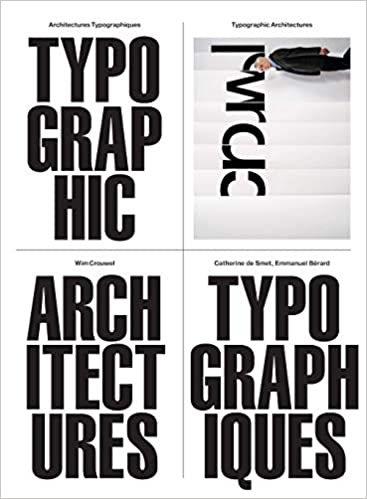
Architectures typographiques. Cet ouvrage est une réédition réactualisée de la version parue pour la première fois en 2007 à l'occasion de l'inauguration de l'exposition " Wim Crouwel, Architectures typographiques : 1956-1976 " à la galerie Anatome à Paris.
Figure majeure du design graphique européen contemporain, Wim Crouwel (1928-2019) a marqué l'histoire de la discipline par sa pratique étendue du design, appliquée tant au domaine culturel qu'au domaine commercial. Au cours de sa carrière, il a réalisé à la fois des travaux de création typographique, des identités visuelles, de la signalétique, des affiches, des travaux d'édition, ou encore la scénographie d'expositions.
Il a également été directeur du Boijmans Van Beuningen Museum de Rotterdam entre 1985 et 1993. Cet ouvrage constitue la première publication en langue française sur le travail de Wim Crouwel, dont l'influence se confirme aujourd'hui auprès des jeunes générations. Dès les années 1950, et durant les décennies suivantes, ce néerlandais, dont le rayonnement dépasse largement les frontières des Pays-Bas, est parvenu à développer une approche de la création graphique alliant l'héritage moderniste à la fantaisie du pop.
A travers trois textes rédigés par Wim Crouwel, Catherine de Smet et Emmanuel Bérard, cet ouvrage témoigne de la diversité de l'oeuvre de Wim Crouwel et revient sur son travail sur les identités visuelles, l'édition, ou la création d'affiches. Abondamment illustré, ce livre se concentre tout particulièrement sur la mise en pages des catalogues réalisés pour des musées tels le Stedelijk Museum d'Amsterdam, ainsi que sur la genèse et la présentation du New Alphabet, créé entre 1964 et 1967.